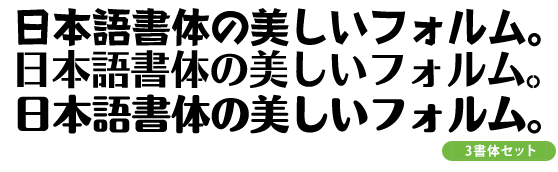
「伝わるインパクトの書体」タイトル・装飾向け3書体パック
MotoyaStAporoLiteN-W6,MotoyaMaAporoLiteN-W8,MotoyaGochikaLiteN-W6
「個性的なサムネで興味を引きたい」「インパクトのある資料にしたい」――そんな時にぴったりの3書体をセットにしました。
モトヤゴチカ、モトヤステンシルアポロ、モトヤ丸アポロは、SNS投稿やYouTubeサムネイル、営業資料、チラシなどで見せたい言葉をしっかり際立たせます。カジュアルにもビジネスにも使いやすく、幅広い発信シーンに対応できる、実用性と表現力を兼ね備えた書体セットです。視認性・インパクト・個性を重視した、太めで存在感がありインパクトのあるデザインが可能です。